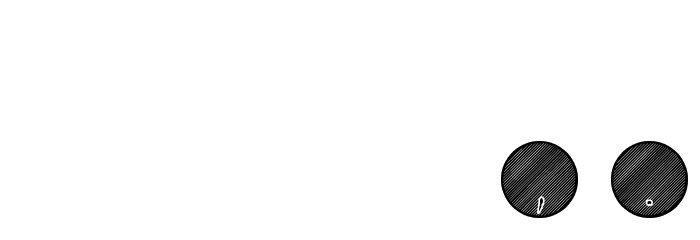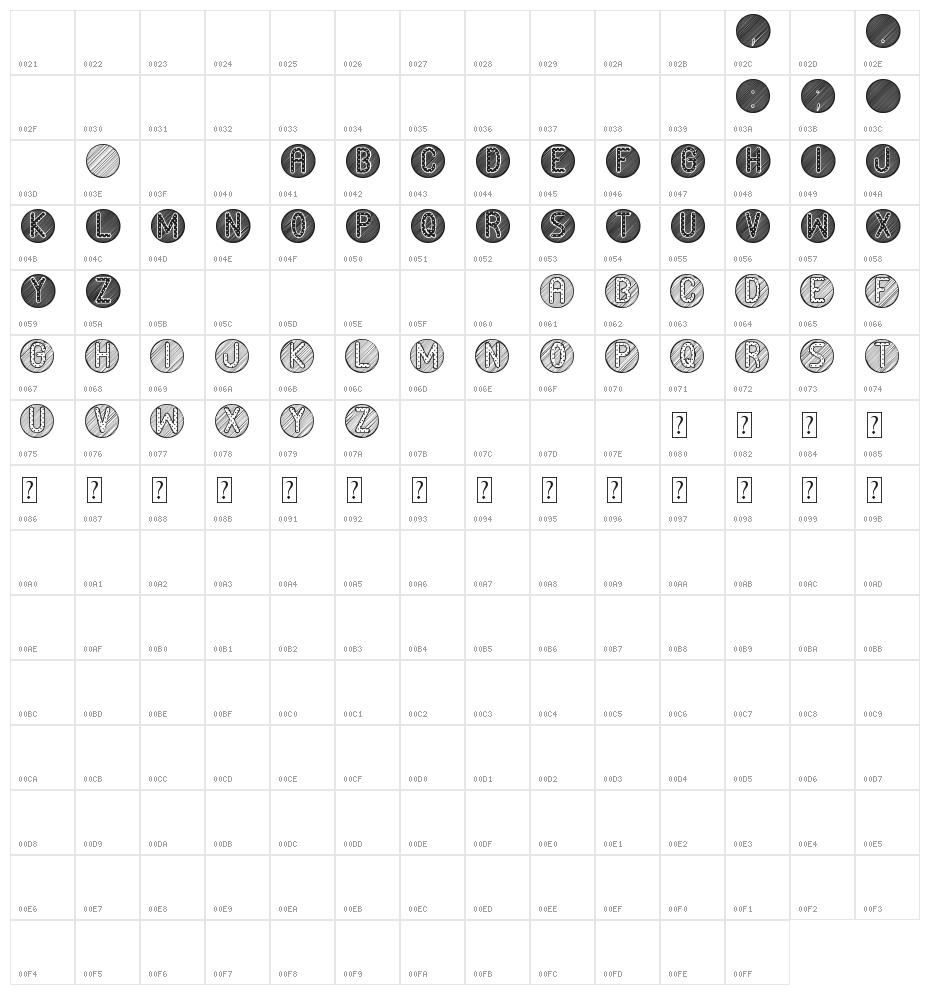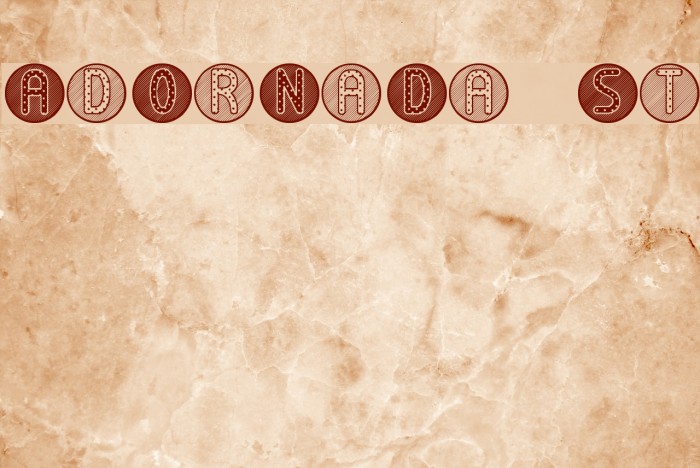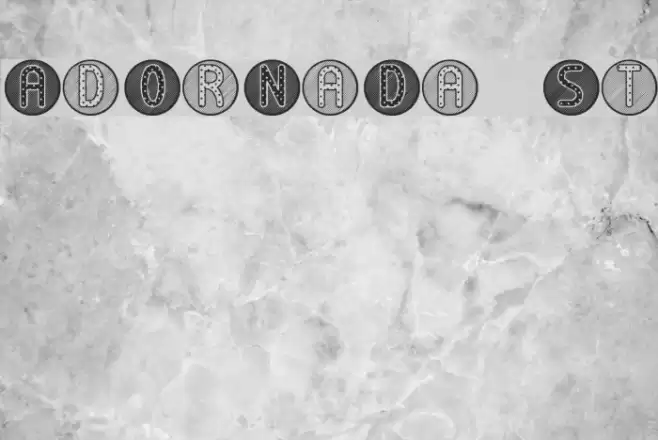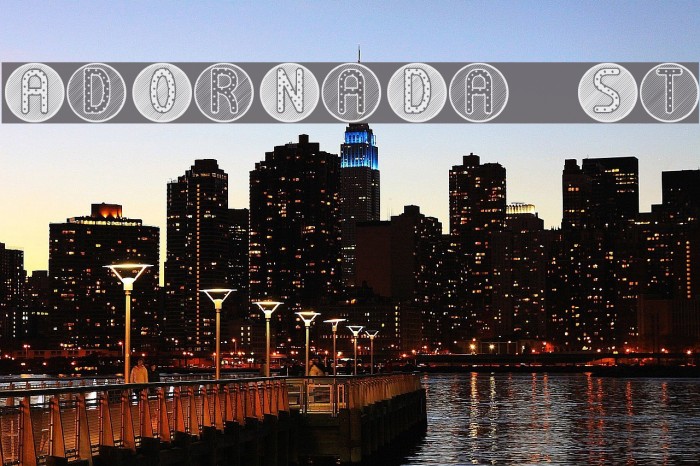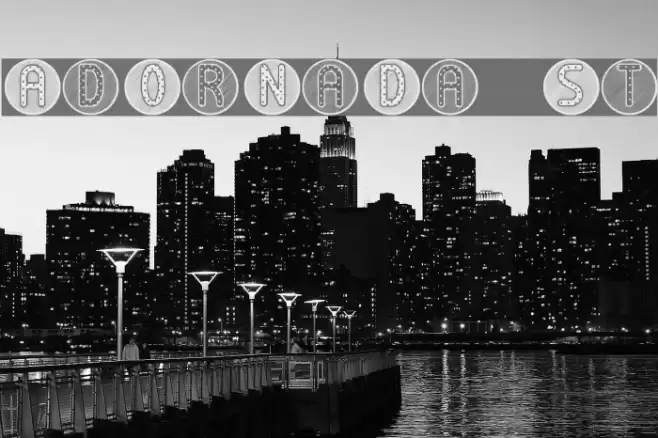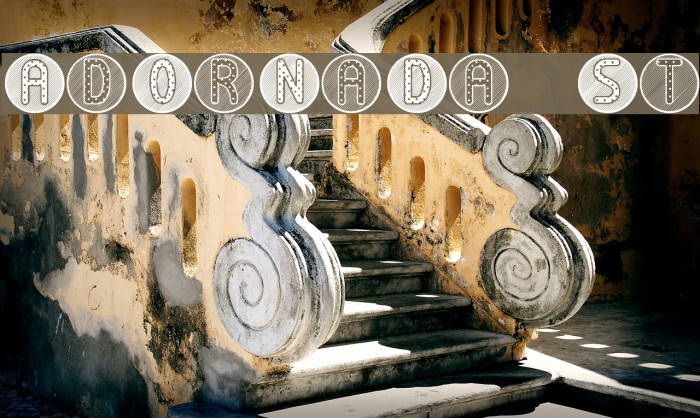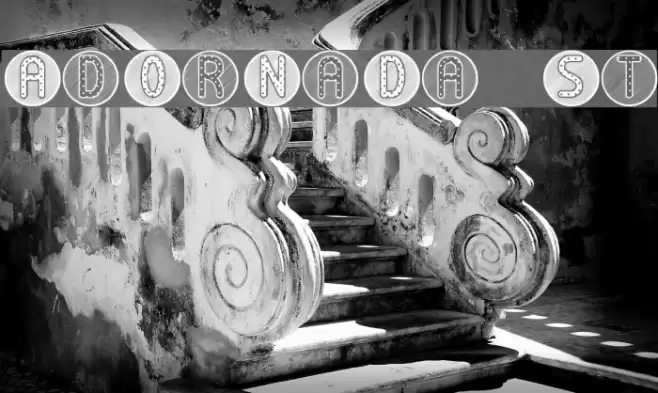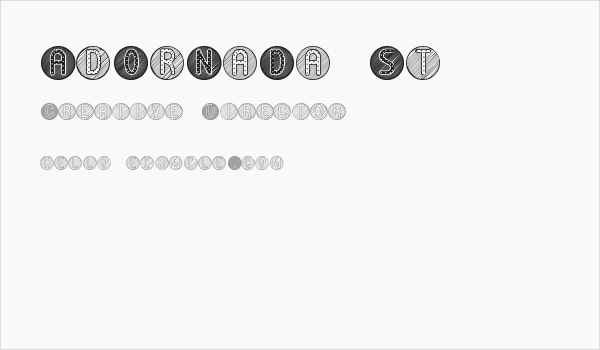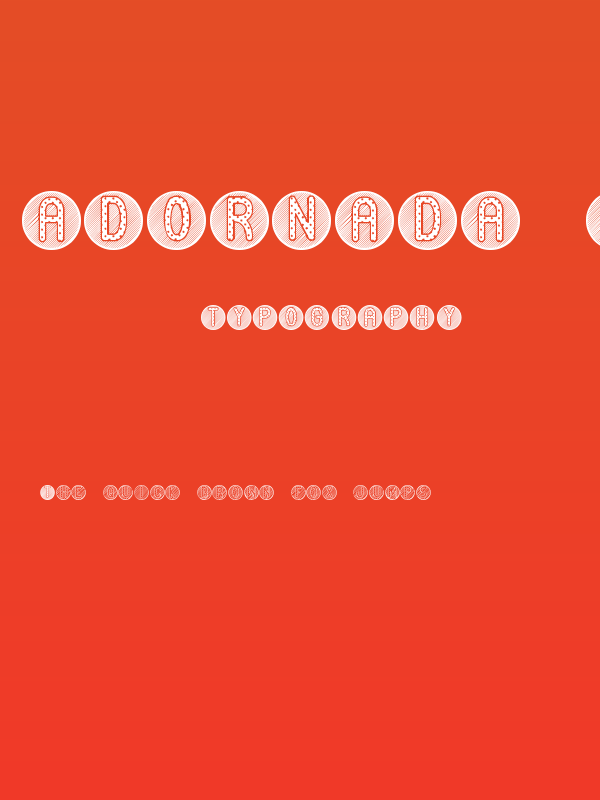
AdOrNaDa St Font
✎ Decorative
| Область применения | Logos, Posters, Invitations |
| Рекомендуемые проекты | Ideal for creative projects such as posters, invitations, and branding materials that require a unique and artistic touch. |